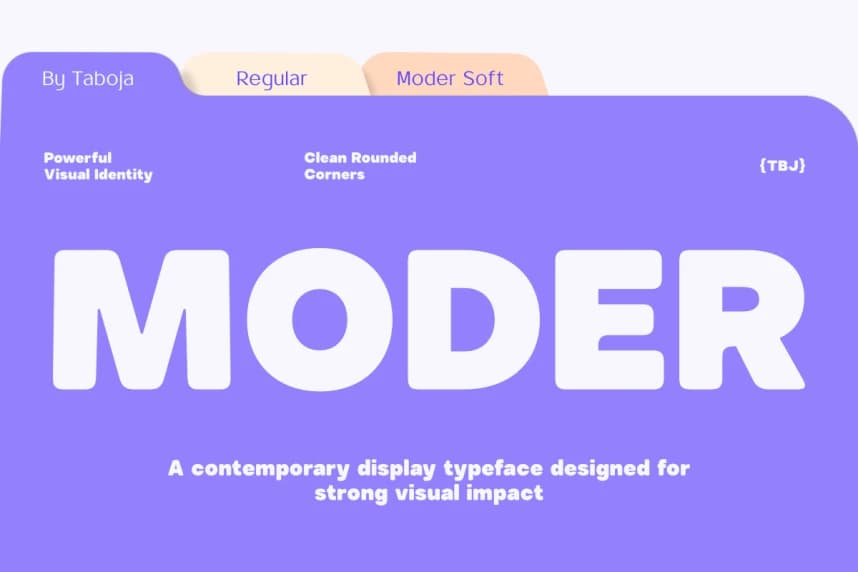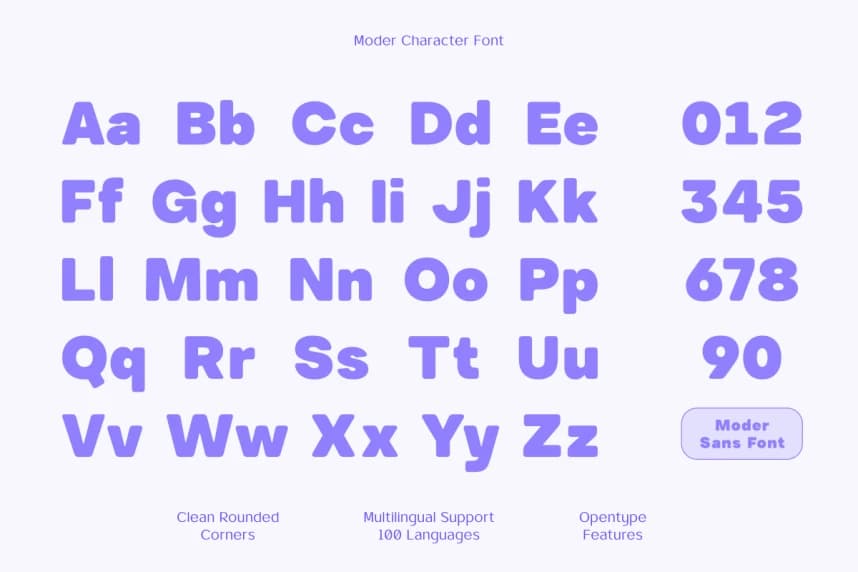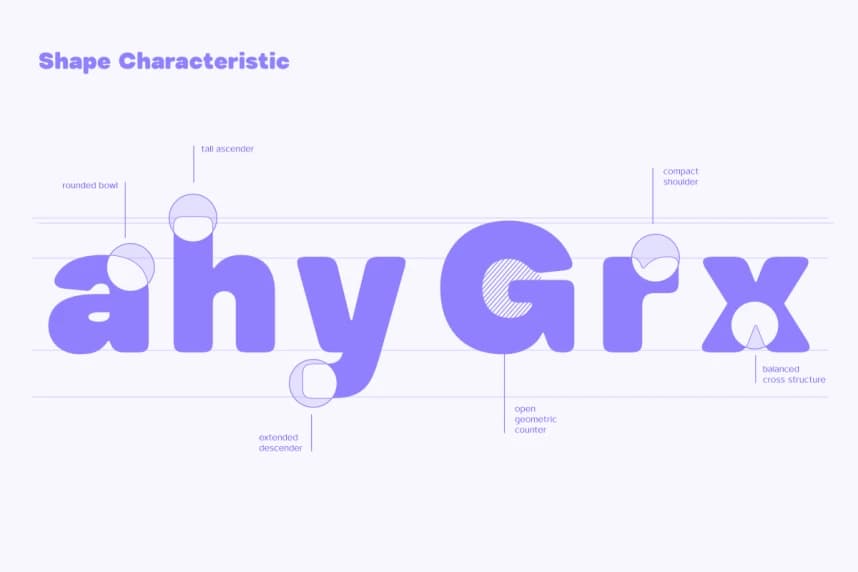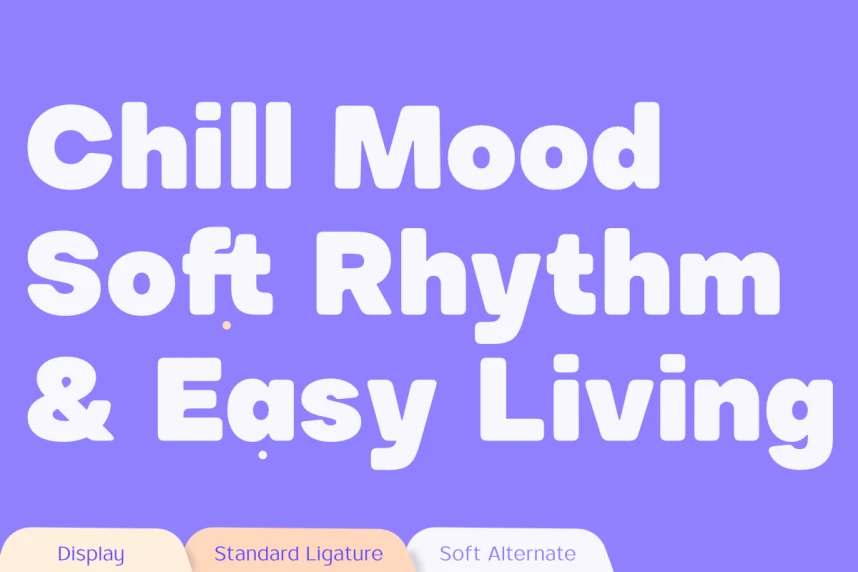
Moder Font
MODER FONT – Contemporary Rounded Display Typeface, çağdaş bir yuvarlak gösteri yazı tipidir ve cesur ile modern bir görsel kimlik sunmak üzere tasarlanmıştır. Akıcı eğriler ve temiz, yuvarlak köşelerle tasarlanmıştır.
MODER FONT – Contemporary Rounded Display Typeface, bir çağdaş yuvarlak gösterim yazı tipi olarak cesur ve modern bir görsel kimlik sunmak üzere tasarlanmıştır. Pürüzsüz eğriler ve temiz yuvarlak köşelerle tasarlanmıştır